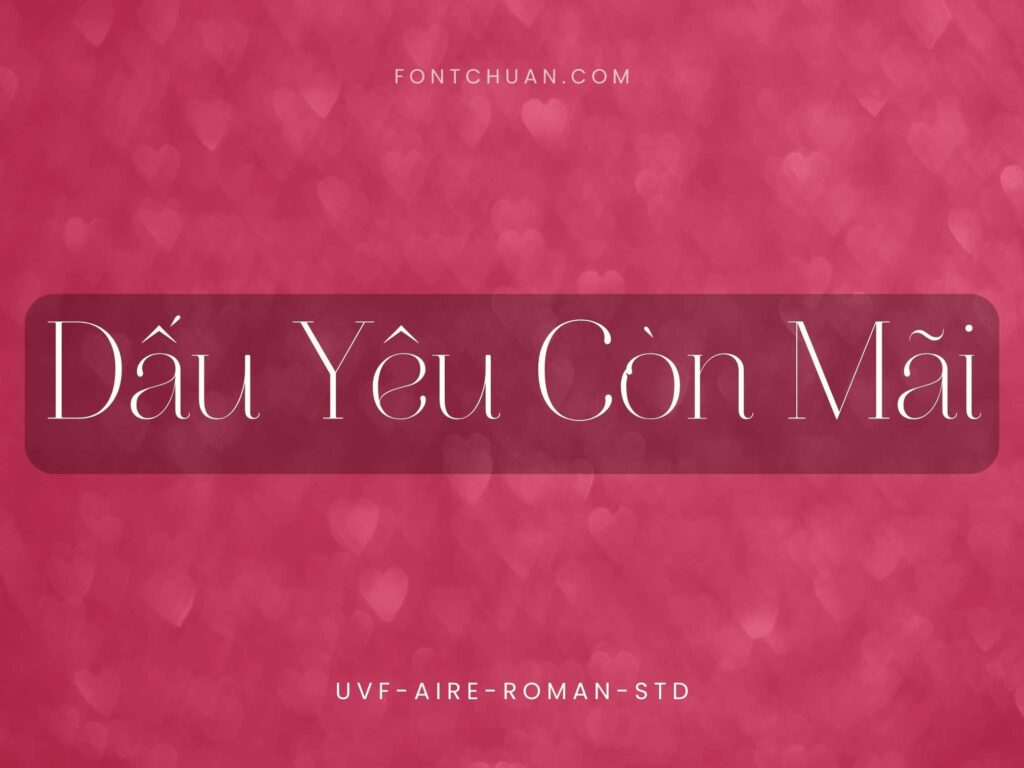
Font UVF Aire Roman Std Việt Hóa
UVF Aire Roman Std là một font chữ serif thanh lịch, mang phong cách cổ điển với các đường nét tinh tế và sắc sảo. Font này được thiết kế để tạo cảm giác trang nhã và chuyên nghiệp, phù hợp cho các dự án như sách, tạp chí, thiệp mời và các ấn phẩm in ấn khác. Với sự kết hợp giữa tính thẩm mỹ và khả năng ứng dụng cao, UVF Aire Roman Std giúp các thiết kế trở nên nổi bật và thu hút hơn.
Font này được sưu tầm và đăng bởi thành viên của Font Chuẩn. UVF Aire Roman Std hỗ trợ đầy đủ các ký tự tiếng Việt, mang lại trải nghiệm sử dụng hoàn chỉnh cho người dùng. Ngoài ra, font này còn hỗ trợ nhiều ngôn ngữ khác, mở rộng khả năng ứng dụng trong các thiết kế quốc tế. Với sự kết hợp giữa tính thẩm mỹ và khả năng ứng dụng cao, UVF Aire Roman Std phù hợp cho các thiết kế thiệp cưới, tiêu đề sách, poster và các ấn phẩm nghệ thuật khác.